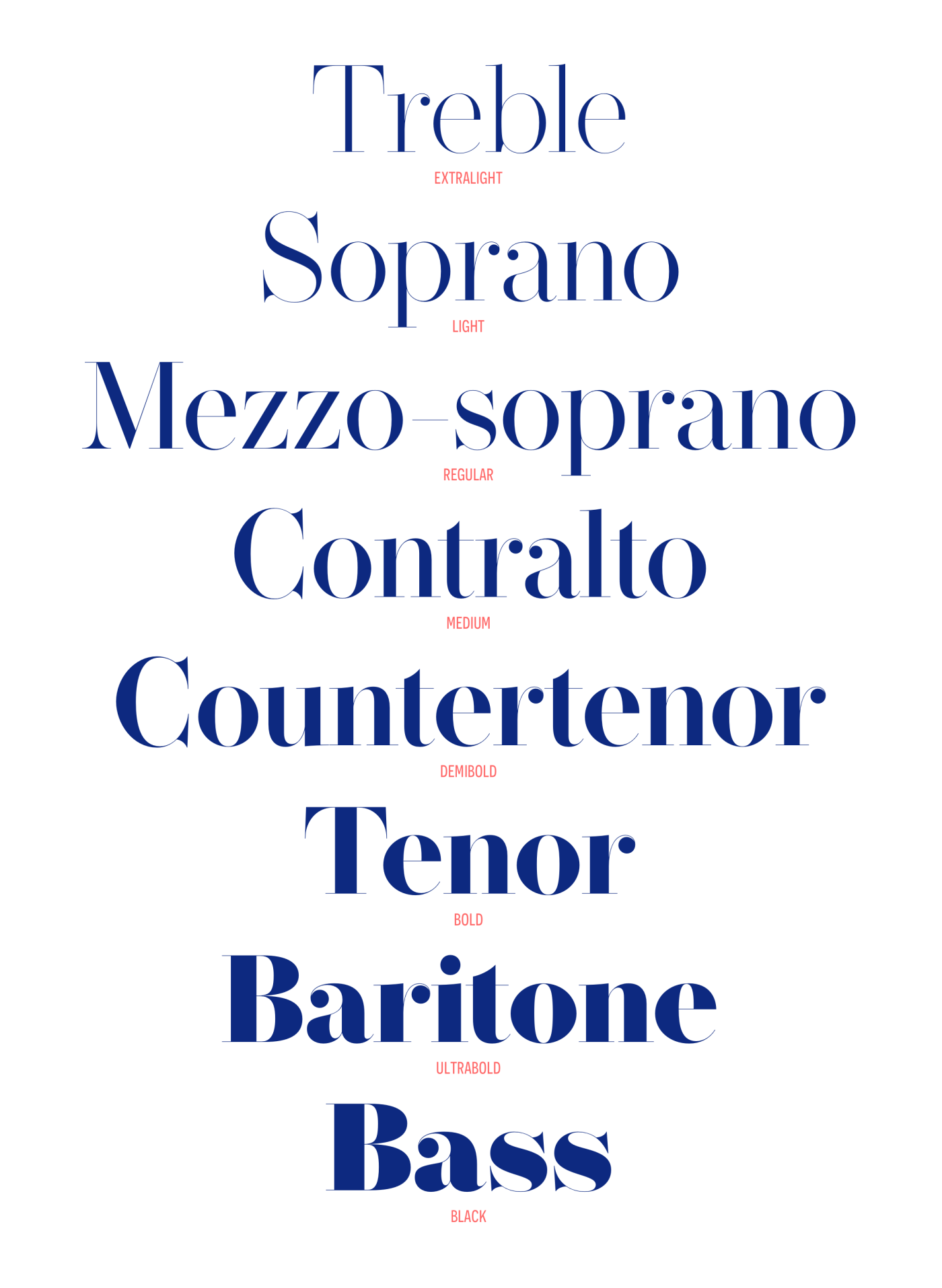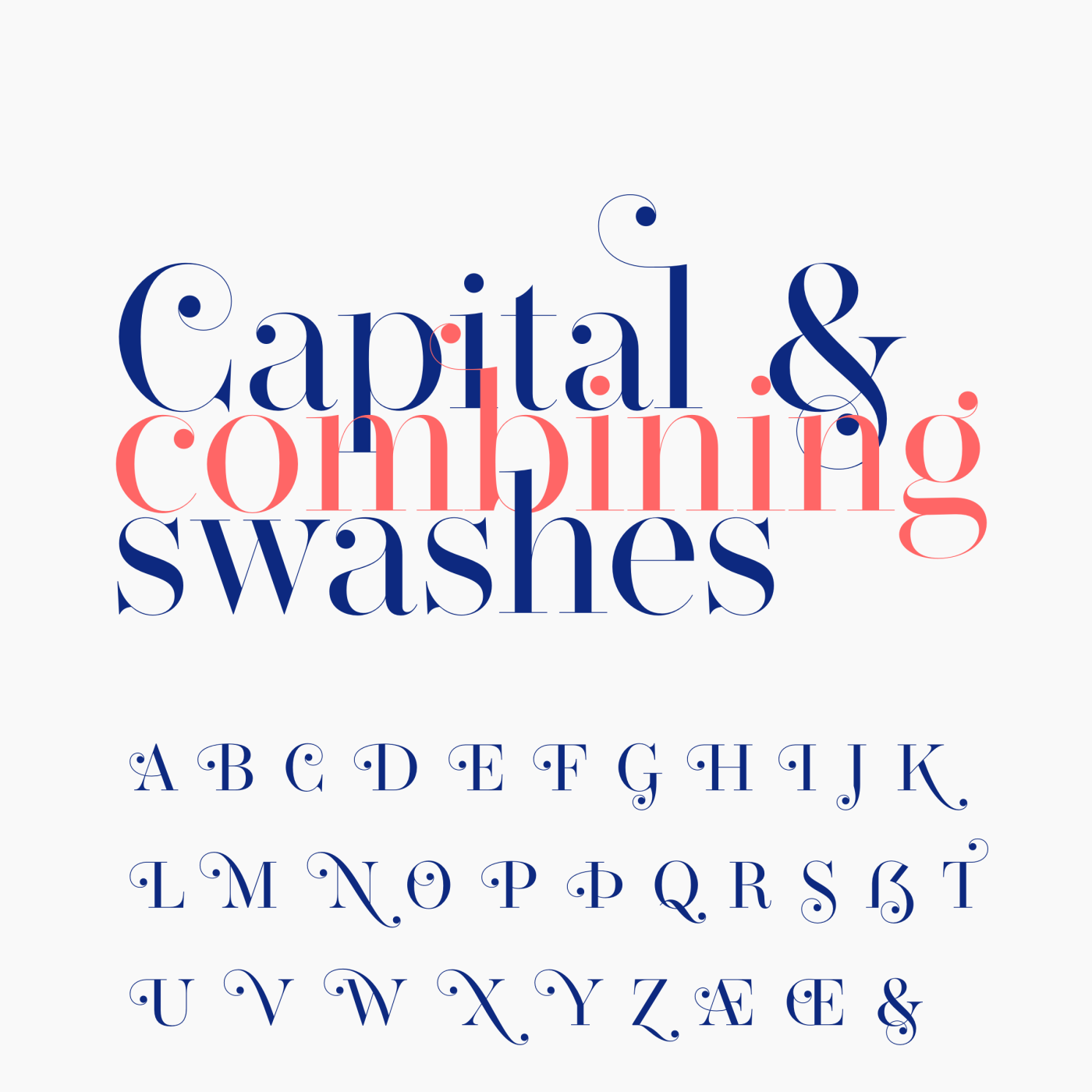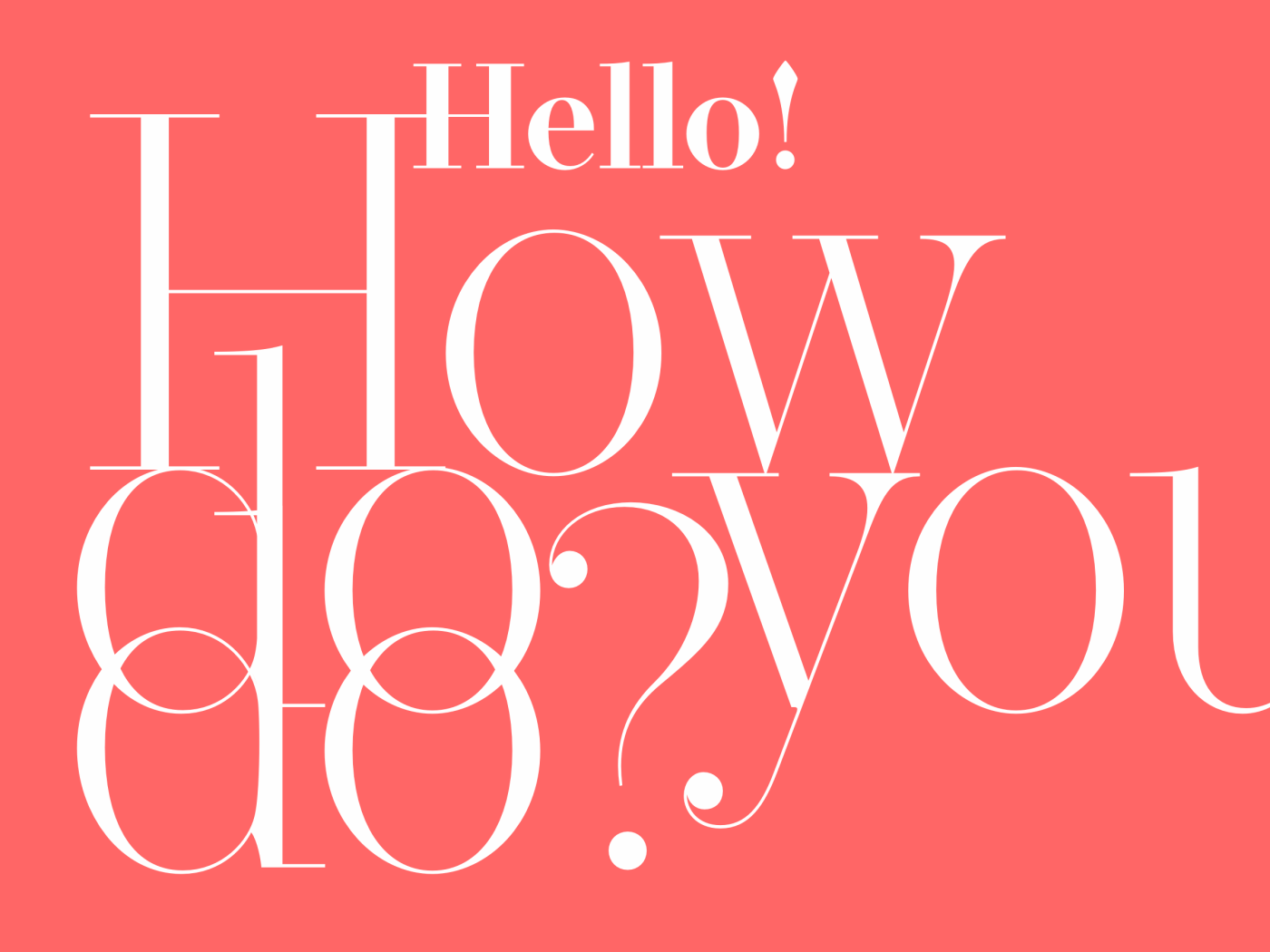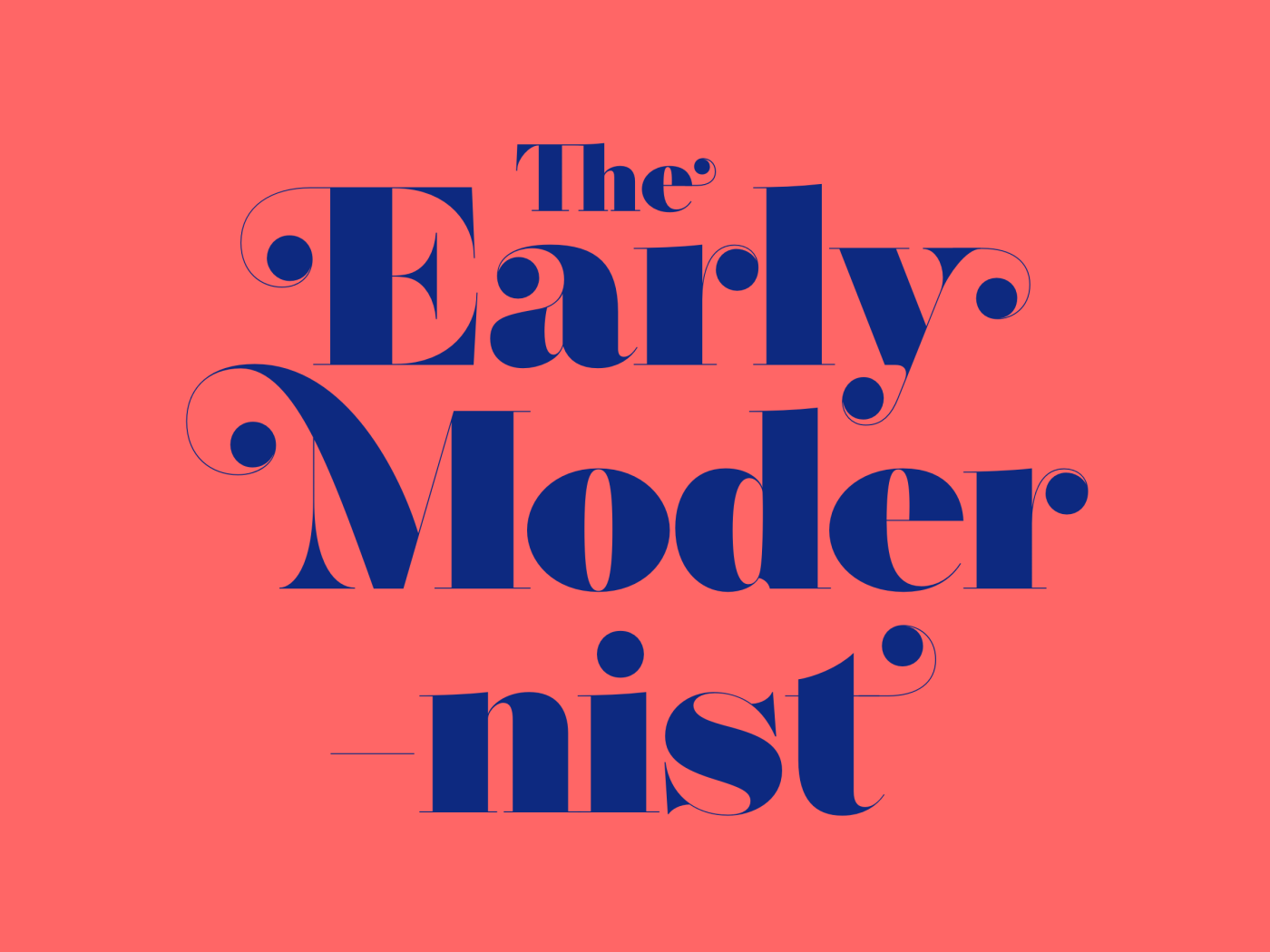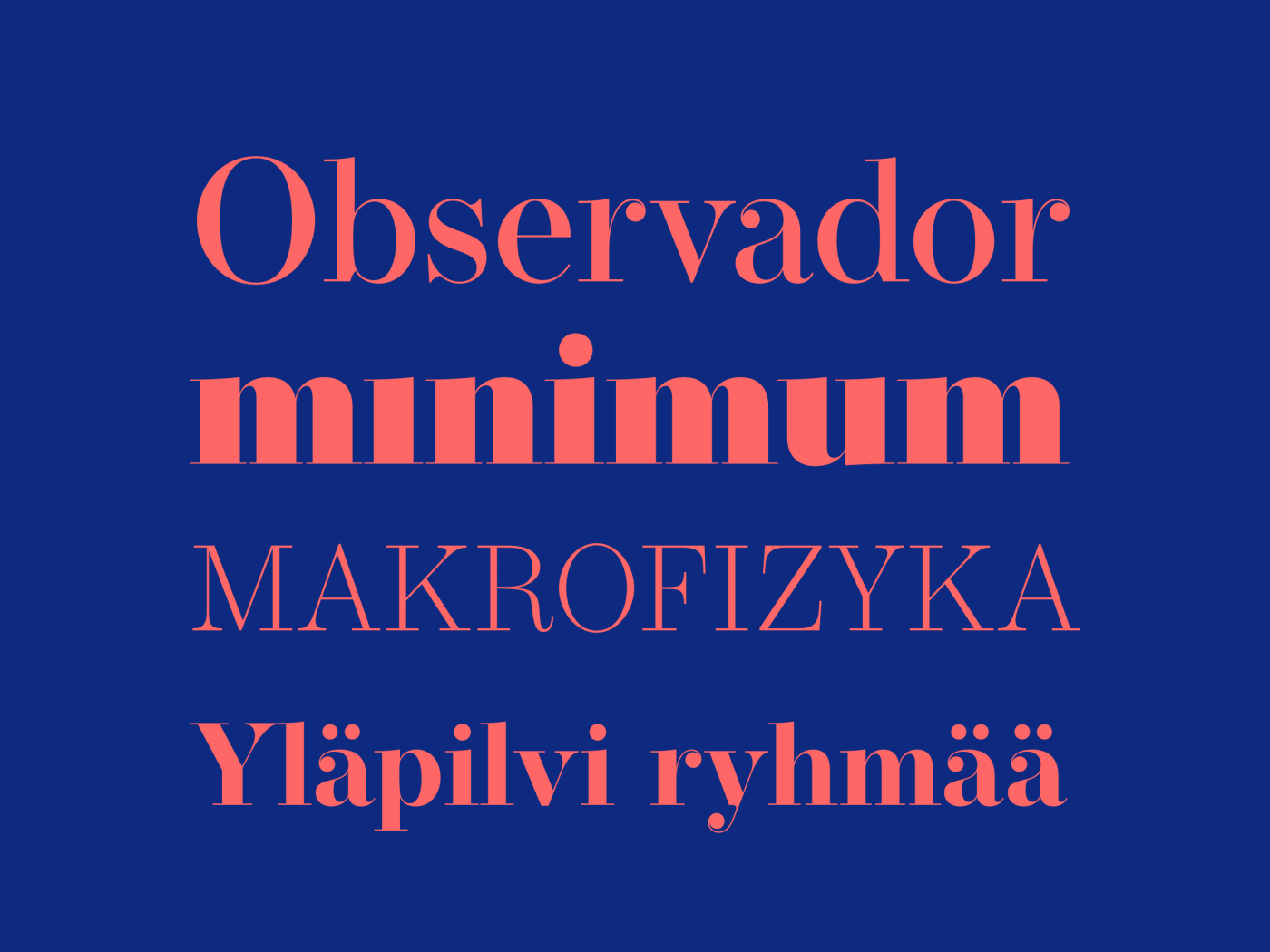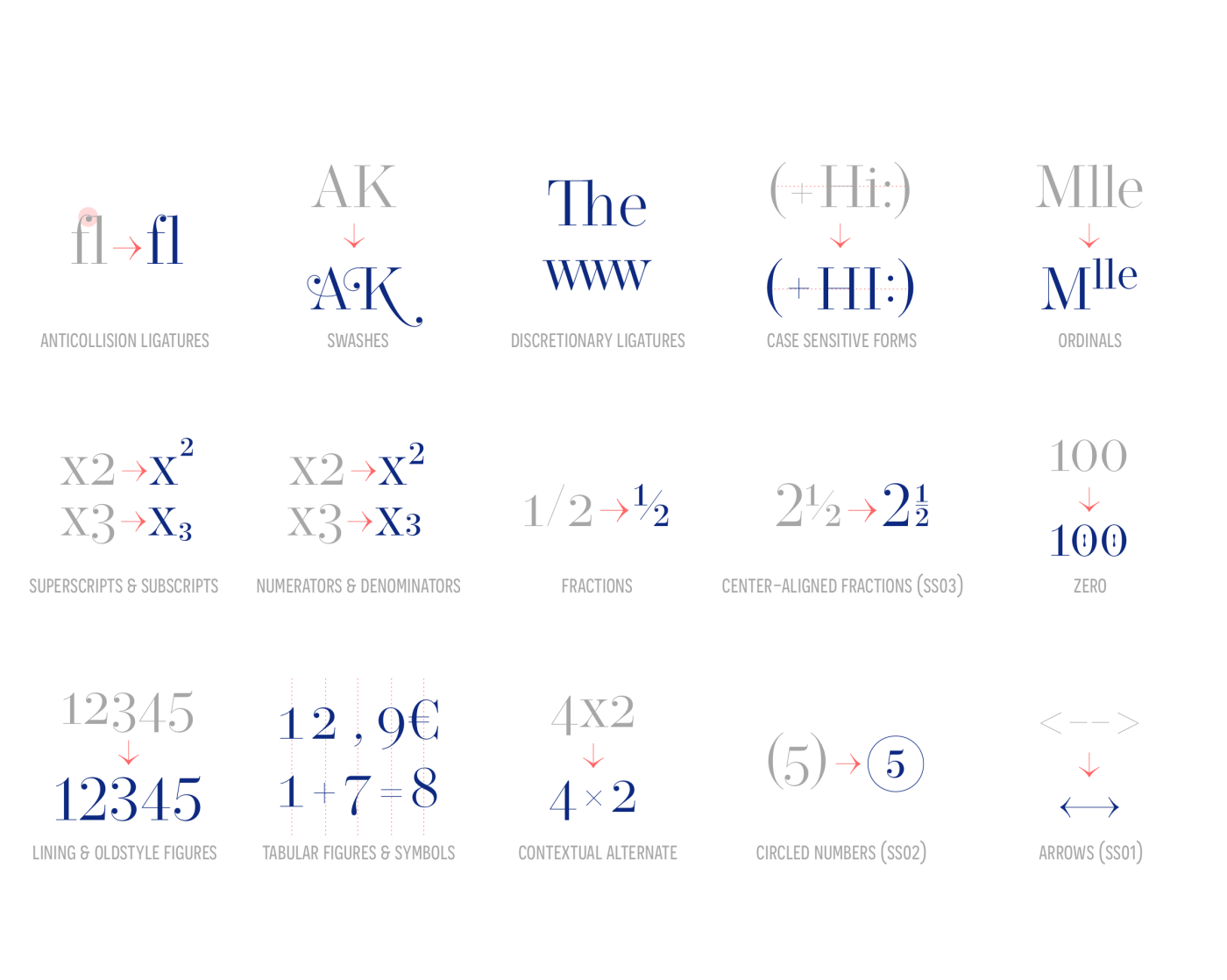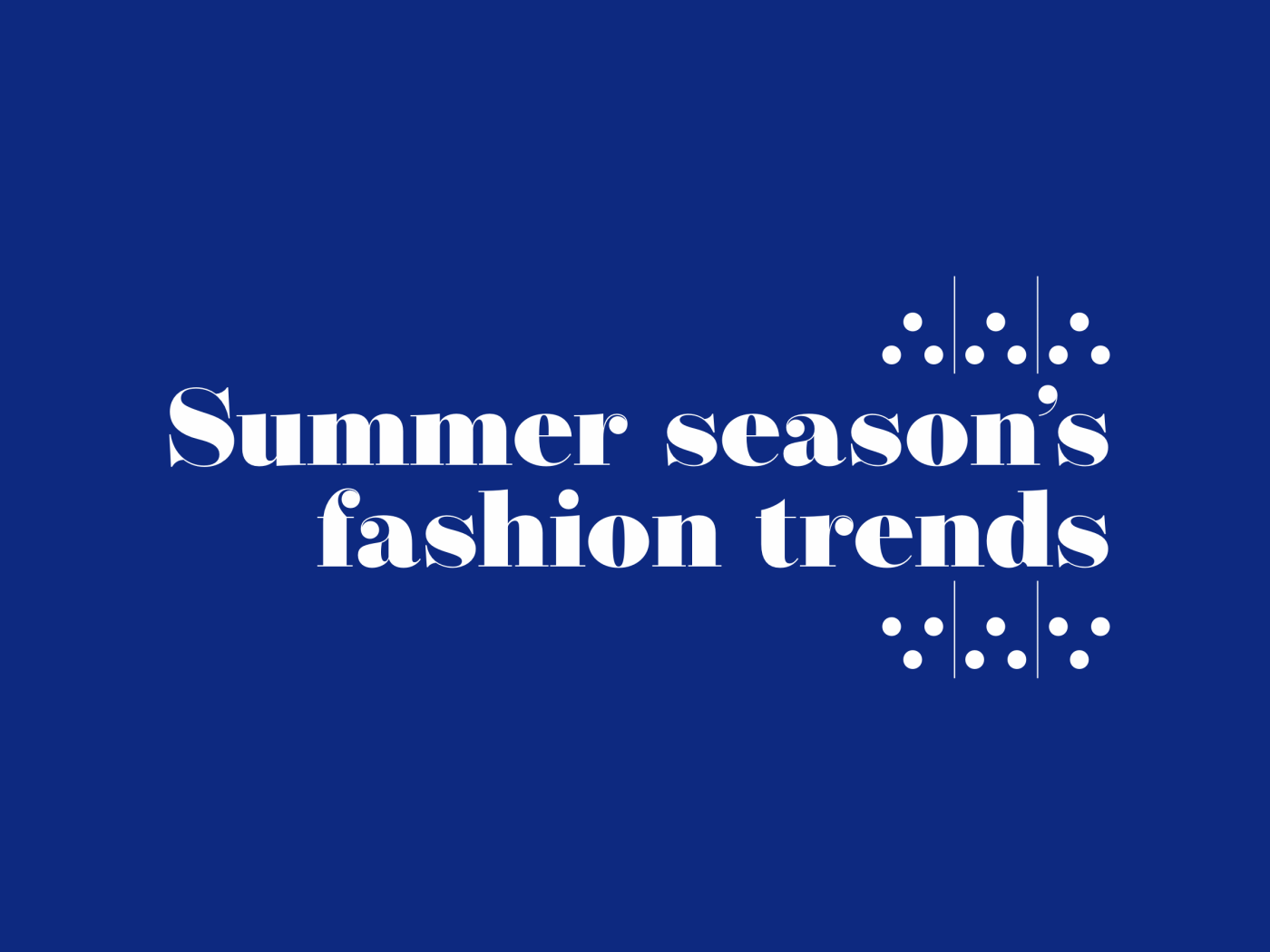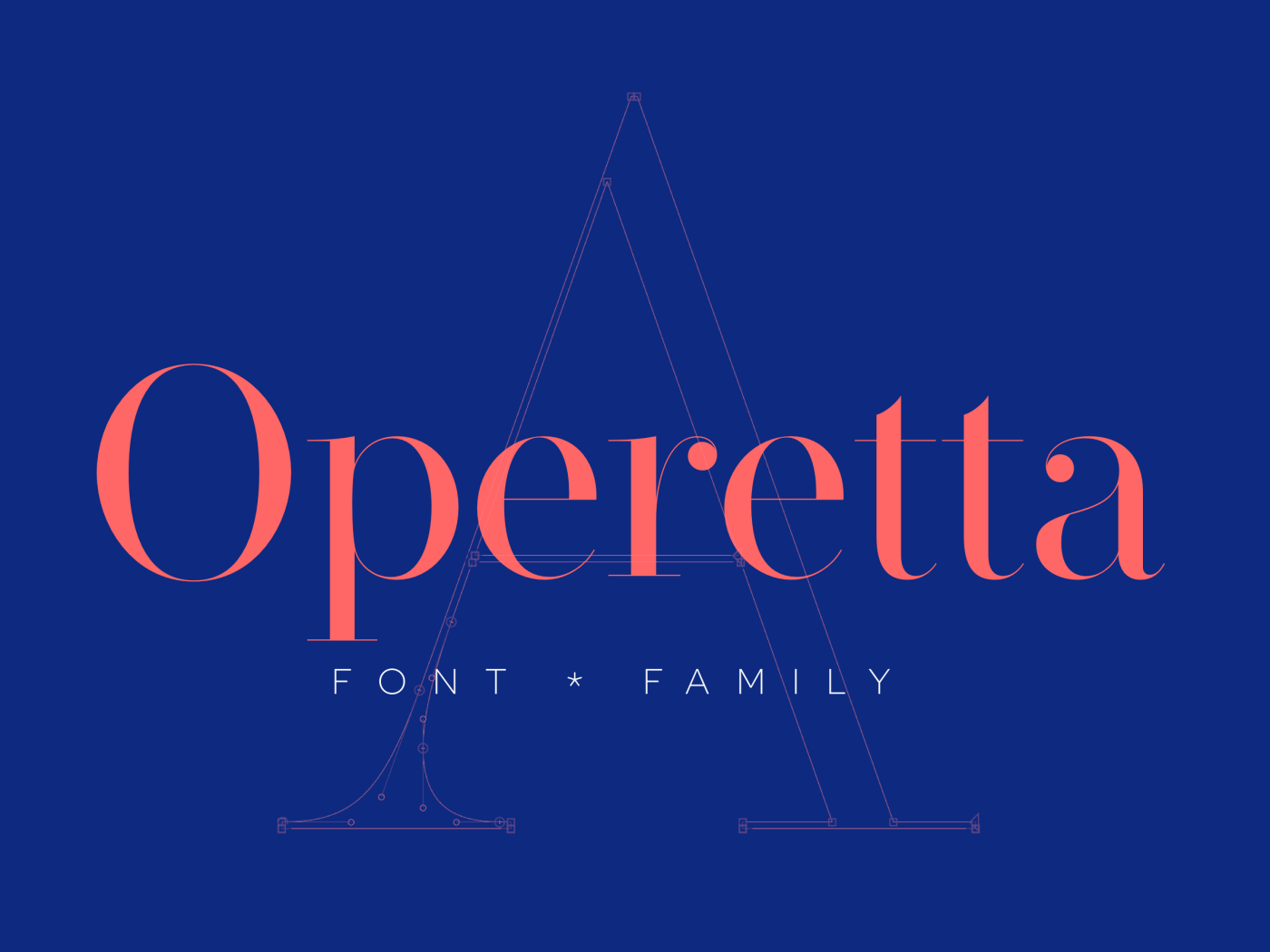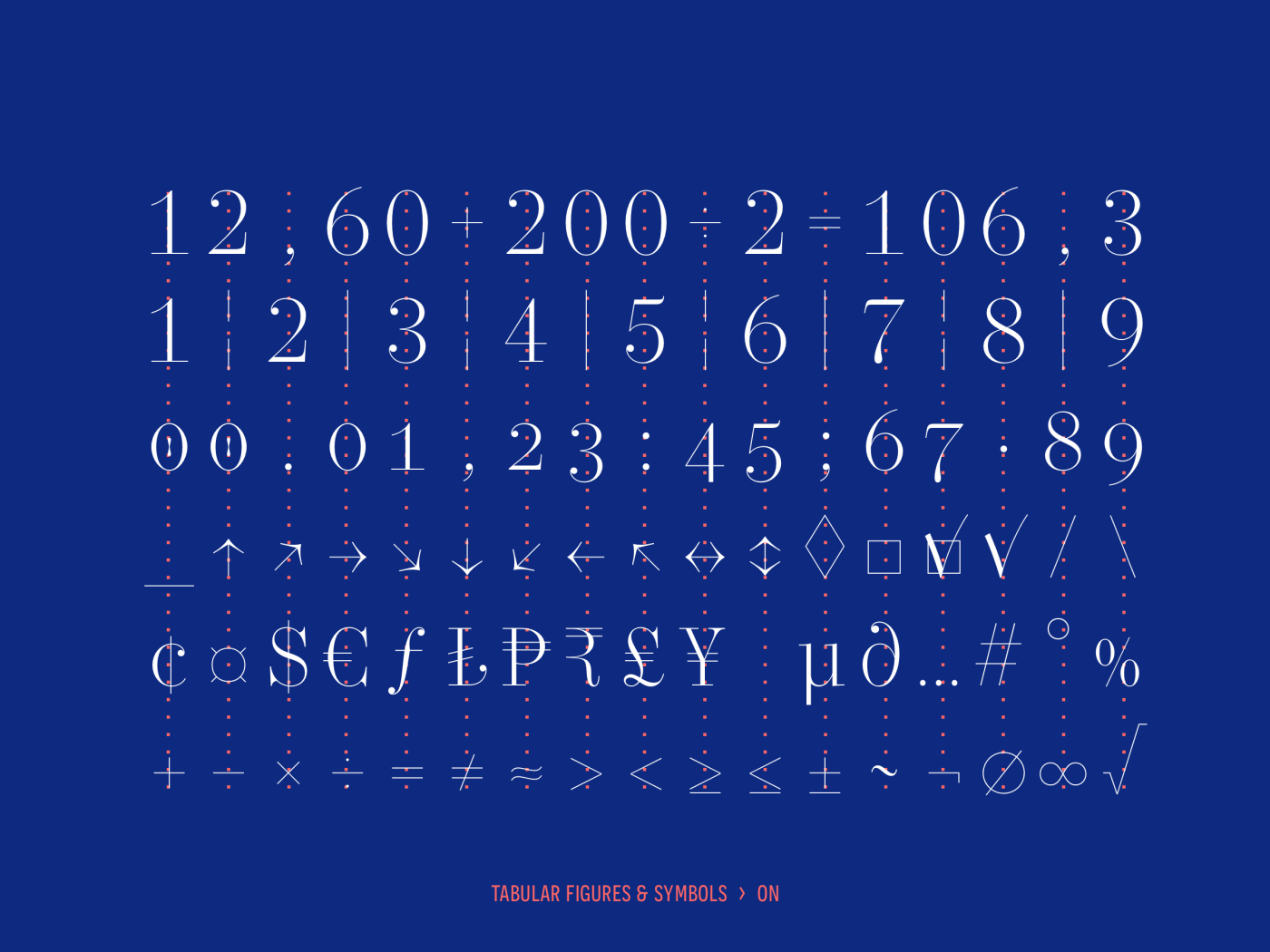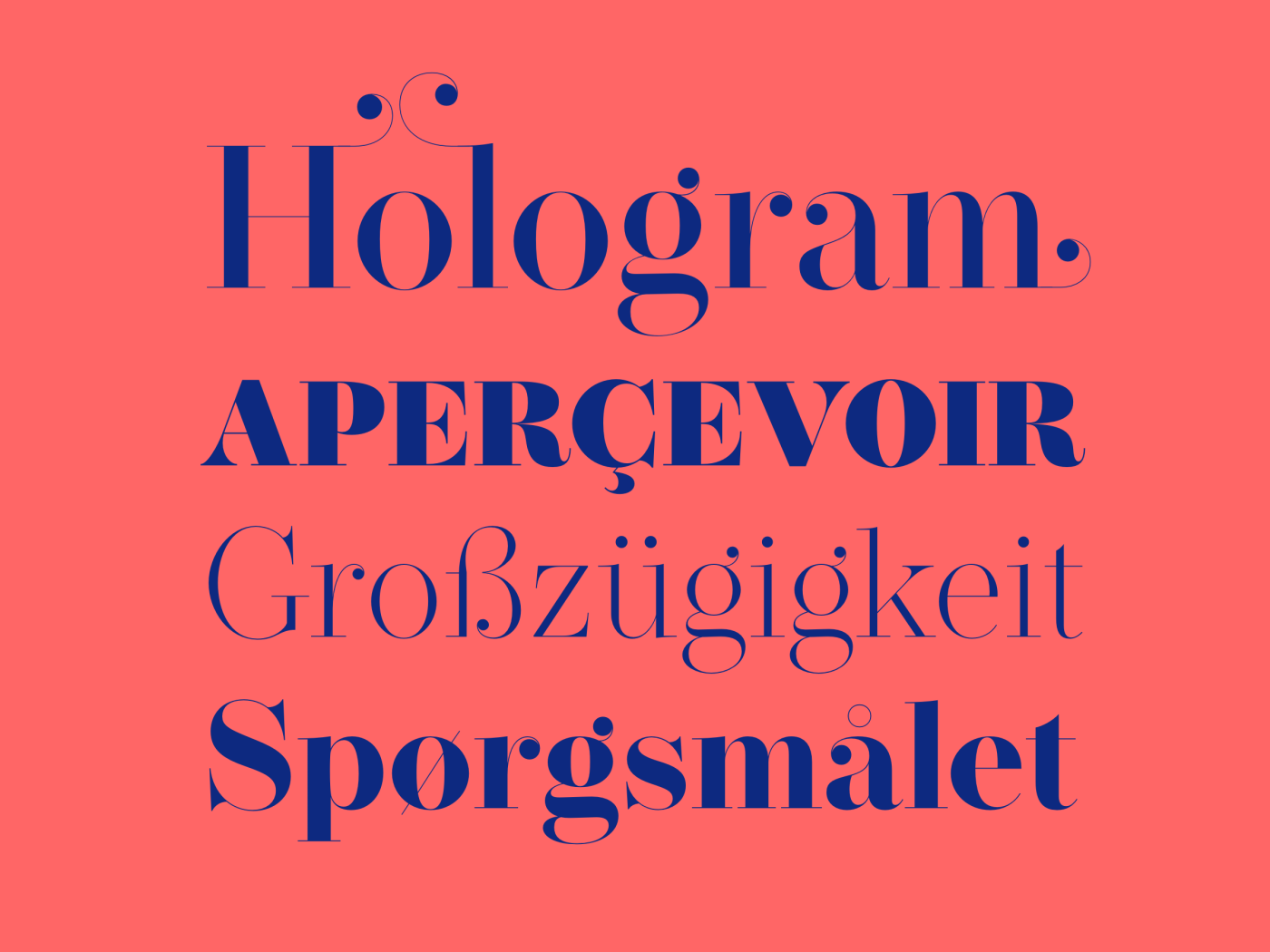
Operetta
Création d’une nouvelle famille de caractères d’inspiration néoclassique (Bodoni, Didot, Walbaum, etc.) en 40 graisses et tailles optiques.
Jan Tonellato